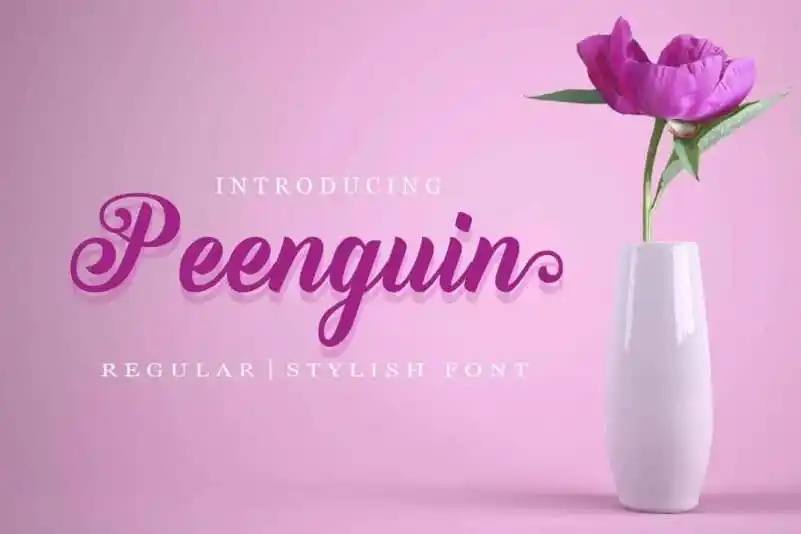
Peenguin Script Font – Download Grátis
Olá! Estamos muito entusiasmados em apresentar à você a Peenguin Script Font, uma fonte criada para aqueles que valorizam uma autenticidade natural nas criações digitais. Este script foi projetado para capturar o brilho do texto real, com aquela delicadeza única na maneira de escrever. Idealmente feito para aplicação em logotipos e outras formas formais como convites, rótulos, selos, revistas, livros, cartas de aniversário ou casamento, embalagens, moda, maquiagem, estofados e materiais de escrita, a Peenguin Script Font está destinada a qualquer tipo de uso publicitário. Essa fonte foi criada por um talentoso designer chamado fontkong, que entregou um produto único, repleto de autenticidade e naturalidade na forma em que os textos são escritos. Com o seu traçado fluido e elegante, a Peenguin Script Font pode transformar qualquer projeto de design no qual ela é aplicada em algo verdadeiramente especial. Talvez esteja hora de adicioná-la à sua seleção de fontes! A Peenguin Script Font oferece um toque personalizado para seus trabalhos digitais.